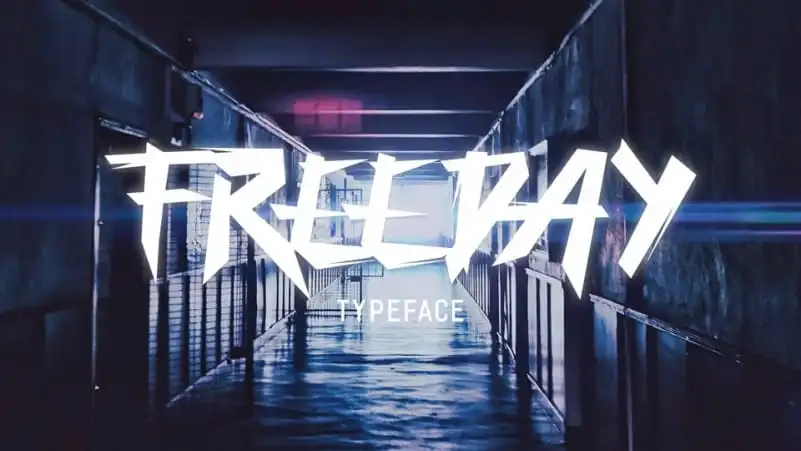
A Freeday Brush Font é uma fonte bold de display com seu charme único que se destaca facilmente nas várias projetos de design. Sua elegância e modernidade fazem dele um ícone perfeito para qualquer tipo de projeto gráfico, desde os grandes headlines até as capas de filmes e músicas, ou até mesmo peças de merchandising. Integrada à sua marca através do estilo urbano e desafiador que define este fonte, a Freeday Brush é uma excelente escolha para quem busca um forte impacto visual em suas criações. A freetype é uma letra escrita à mão, o que contribui significativamente para seu ar inovador e único. É importante notar que esta fonte possui apenas letras maiúsculas, mas ainda assim oferece a versatilidade necessária para criar designs impecáveis. O designer Haris Prawoto criou essa fonte inspirada no estilo urbano e na cultura de rua, dando ao público uma opção de fonte visualmente atraente e desafiadora. Esta é uma ótima escolha para quem deseja destacar sua marca ou produto em ambientes visuais impactantes como capas de mídias sociais, materiais promocionais e embalagens de produtos. Com seu design cuidadosamente pensado e seu estilo inovador, a Freeday Brush Font certamente se tornará uma opção preferencial para designers gráficos em busca de uma fonte forte e distintiva.